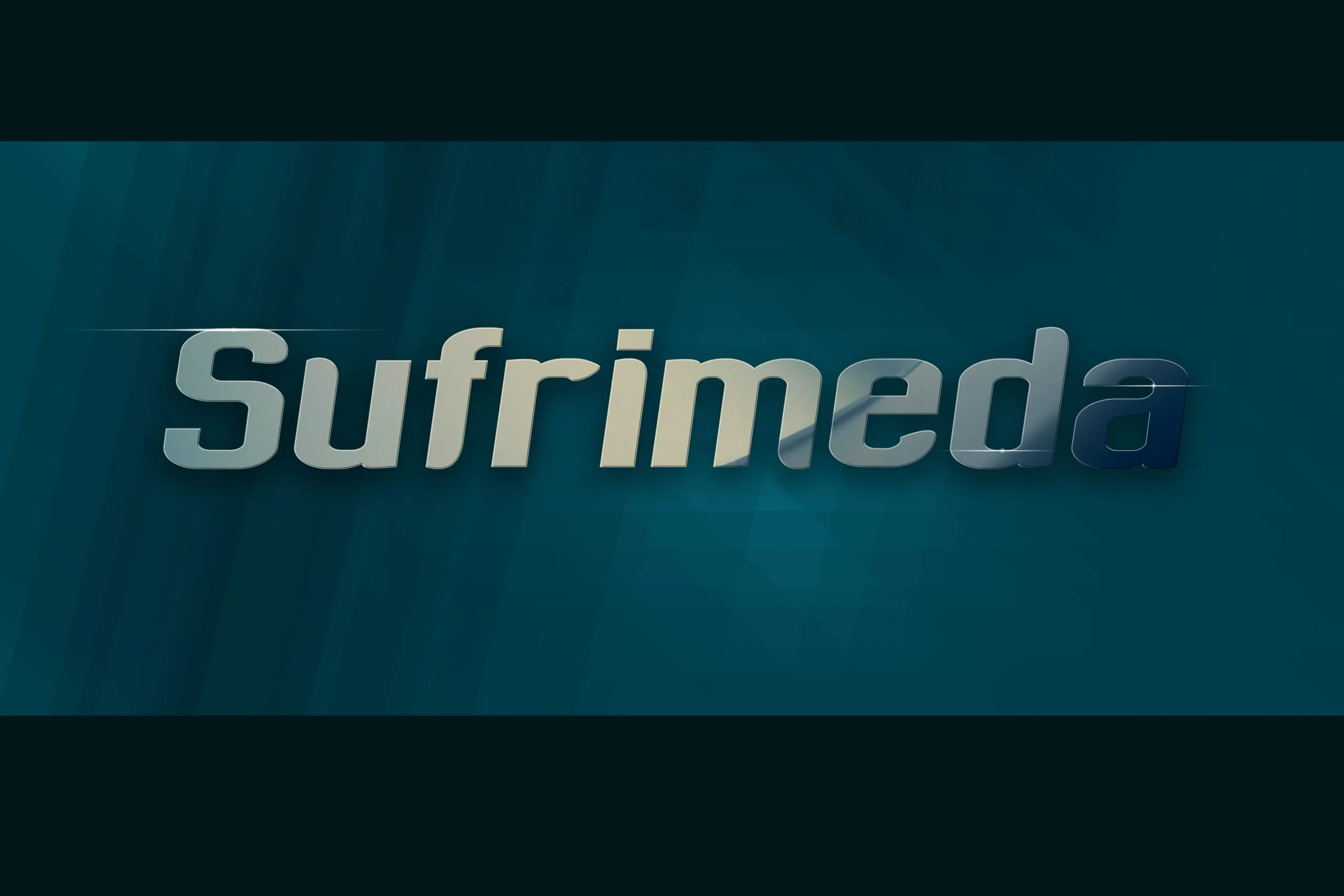
A Sufrimeda é uma fonte de display geométrica que se destaca para seu uso em grandes textos ou títulos. Esta elegante escolha de tipo moderna e minimalista encaixa perfeitamente no mundo do design gráfico, oferecendo um visual atraente sem perder nenhuma das funcionalidades essenciais. Ideal para criações que exigem destaque visual em ambientes digitais, seja em banners ou portfólios online, a Sufrimeda é uma escolha confiável e profissional. Com seu formato geométrico clássico, esta fonte combina modernidade com um toque de sofisticação, tornando-a um recurso indispensável para designers que desejam destacar seus projetos em meio ao caos visual da web. Adaptada a qualquer projeto, seja ele complexo ou simples, a Sufrimeda manterá sua identidade e estilo visuais com alta qualidade e consistência.